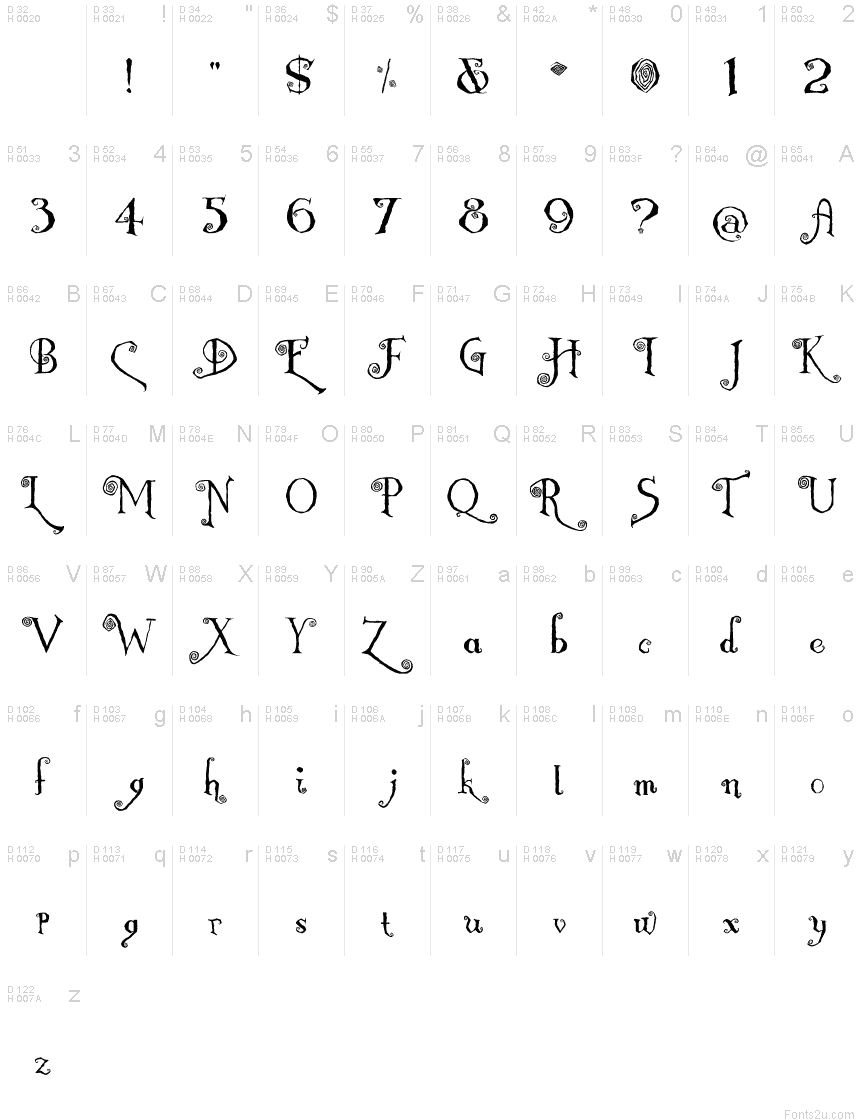
Nemo di Chris Hansen è un font display gratuito e creativo, caratterizzato da volute decorative, ghirigori e una forma serif manoscritta che conferisce alle lettere un tocco fiabesco. Le forme variano da riccioli stretti a ganci più affilati, per un ritmo complessivo ornamentale che non perde mai la sua struttura di base.
Nemo è perfetto per inviti, titoli di poster, loghi, copertine di libri e packaging a tema, dove un accento calligrafico è più efficace di un testo semplice. Questo font gratuito è ideale anche per etichette e intestazioni decorative, perché i dettagli arricciati donano alle parole brevi una finitura distintiva senza bisogno di ulteriori interventi.